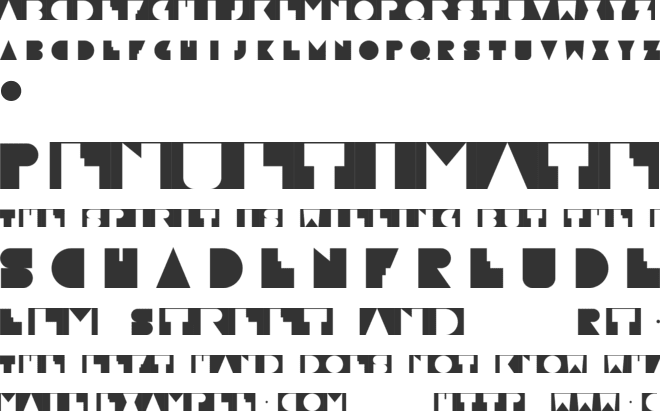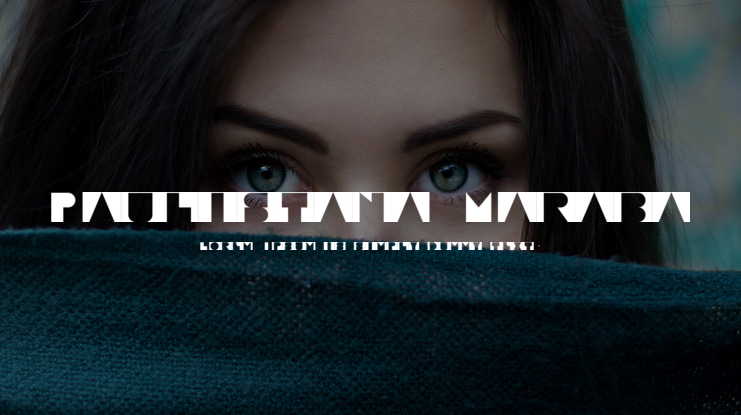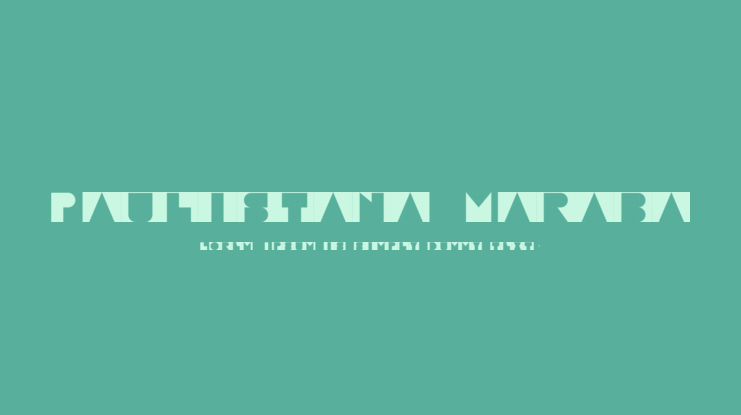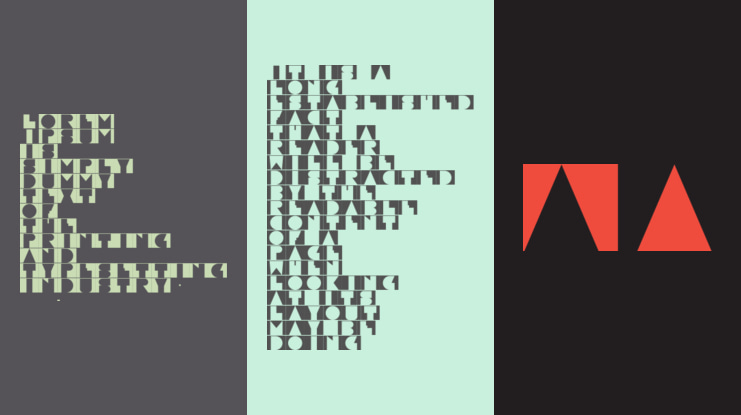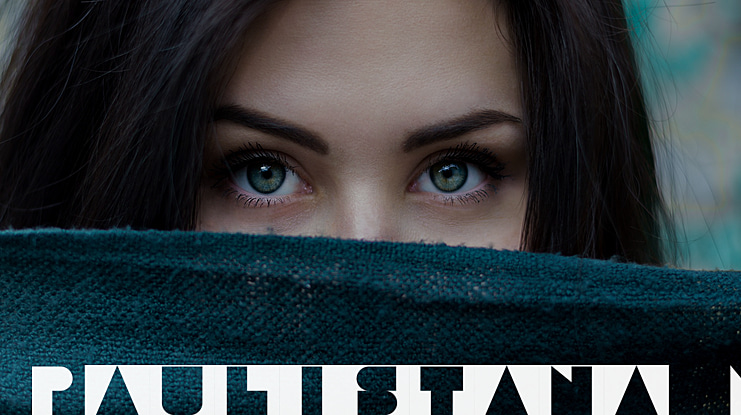
Paulistana Maraba Font
Sérgio Salgadgo
Série Paulistana – Pesquisa sobre a tipografia na arquitetura da cidade de São Paulo (Brasil).
Paulistana Series - Research about the typography in the architecture of the São Paulo city (Brazil).